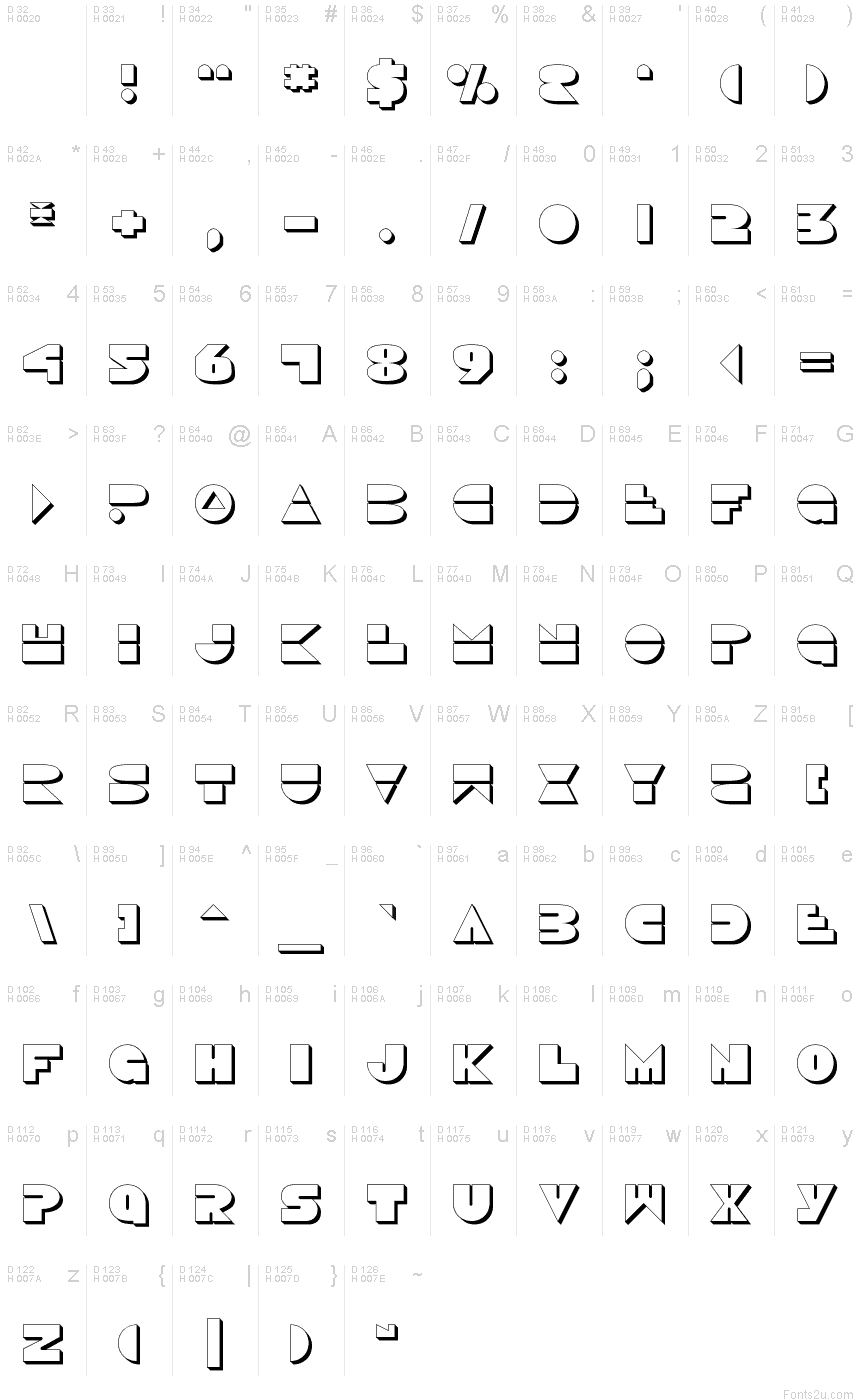
خط Disco Duck 3D من تصميم Daniel Zadorozny التابع لـ Iconian Fonts، هو خط عرض (Display) مجاني يتميز بنمط مبهج وظلال تجعله يبدو وكأنه خرج للتو من حلبة رقص متوهجة. تمنح الخطوط الأنبوبية السميكة والمنحنيات الانسيابية وتأثير التجسيم (3D) المدمج لكل كلمة مظهراً لامعاً ومنحوتاً، يشبه الحروف الكرومية التي تعكس أضواء النوادي الليلية. بصفته جزءاً من عائلة Disco Duck، فهو يحول حتى العناوين القصيرة إلى شعارات رسومية جريئة دون الحاجة إلى أي تنسيق إضافي.
باستخدام Disco Duck 3D، يكتسب نصك فوراً أجواء عناوين حفلات الريترو، مما يجعله مثالياً لملصقات الفعاليات، ومنشورات النوادي، وأغلفة الألبومات أو قوائم التشغيل، وصور مصغرة لفيديوهات يوتيوب، وعناوين الألعاب، وتصاميم الهدايا التذكارية الممتعة. يتألق هذا الخط المجاني حقاً عند استخدامه بحجم كبير مع تباعد أكبر قليلاً، مما يسمح لأشكاله الضخمة بالتنفس. للحصول على تباين مثالي، أرفقه بخط "سانس سيريف" هندسي نظيف أو خط "غروتسك" بسيط في النصوص الفرعية، لتركيز الانتباه على أشكاله المرحة والحيوية.